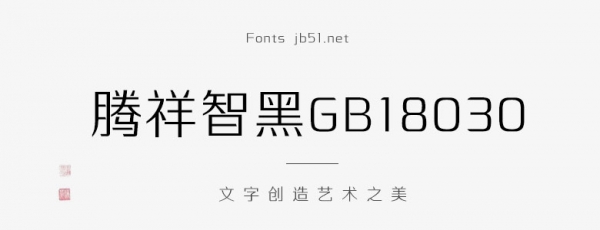
騰祥智黑GB18030合集(W1/W2/W3/W4)是一款不錯的藝術字體,由騰祥字庫出品,該字體筆畫簡潔、硬朗、穩(wěn)重大方,塔形頓點、撇點賦予了智黑特殊的設計效果,適合應用于藝術設計、平面宣傳設計、網頁設計,書法字帖等領域,需要的朋友可以前來本站下載。
騰祥智黑系列字庫是騰祥睿黑系列字庫的兄弟篇,與睿黑風格相近但排版效果迥異。智黑系列更強調了黑體的特征,筆畫簡潔、硬朗、穩(wěn)重大方。塔形頓點、撇點賦予了智黑特殊的設計效果,使智黑又區(qū)別于傳統(tǒng)的黑體,既具有黑體的魅力又具有一定的裝飾特色,使黑體具有了靈活、生動的特點,從而形成自己鮮明的特色。